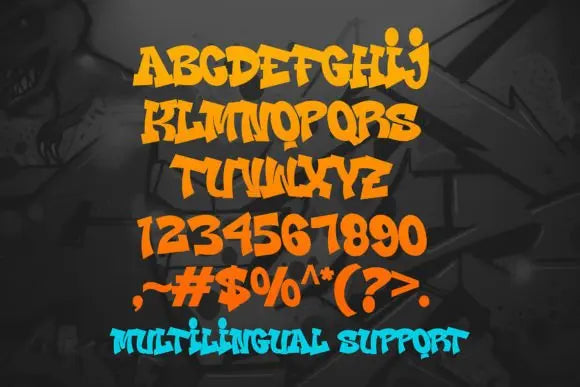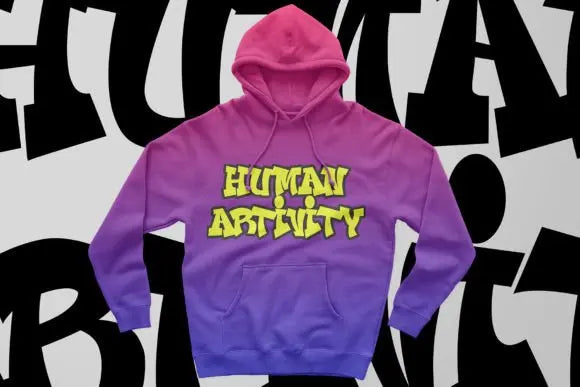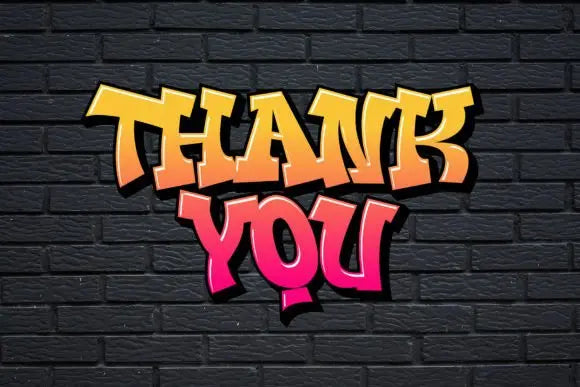
Fuente Fast Blaze
Fast Blaze es una fuente de graffiti urbano caracterizada por bordes afilados y una apariencia atrevida. Ideal para carteles musicales, diseños de indumentaria, camisetas y ropa urbana, esta fuente aporta un toque vanguardista a tus proyectos.
El estilo único de Fast Blaze lo convierte en la elección perfecta para temas de death metal o graffiti urbano.
Ya sea que desee crear una declaración fuerte y poderosa o simplemente agregar un toque de actitud a sus diseños, Fast Blaze es la fuente para usted.